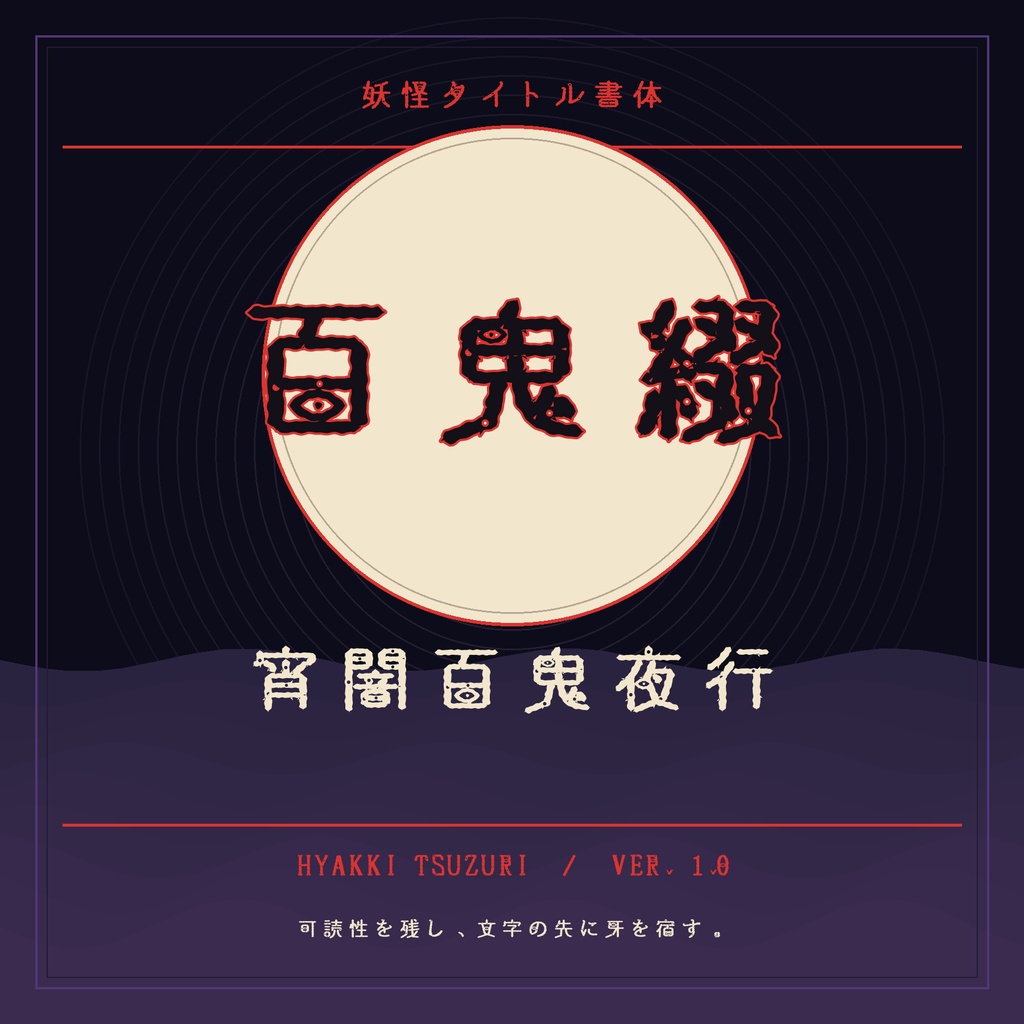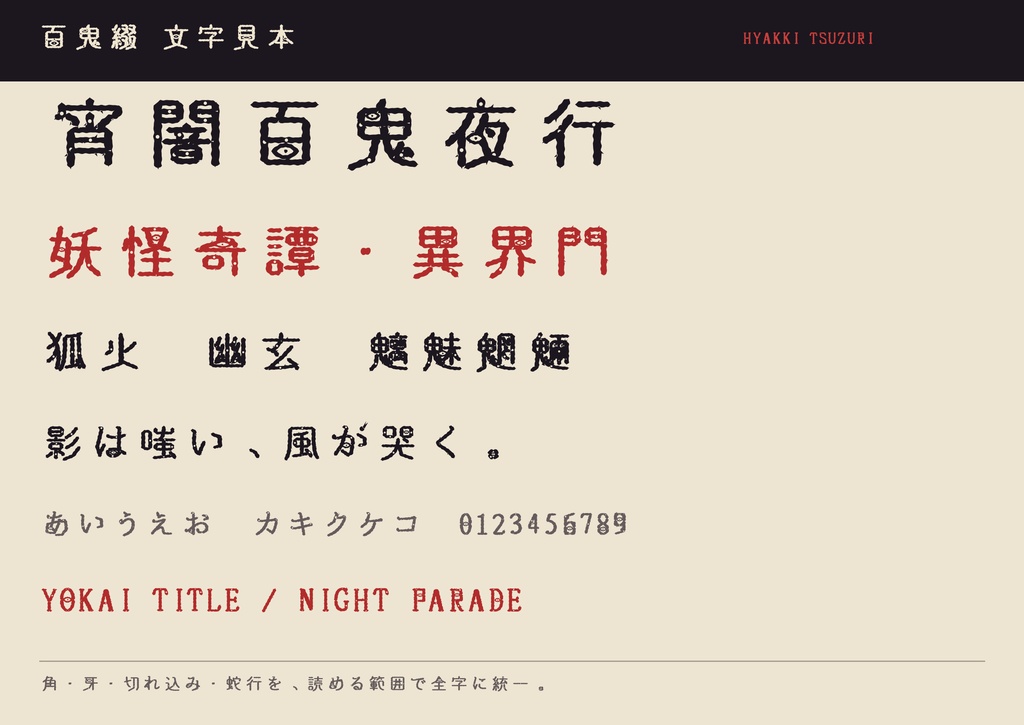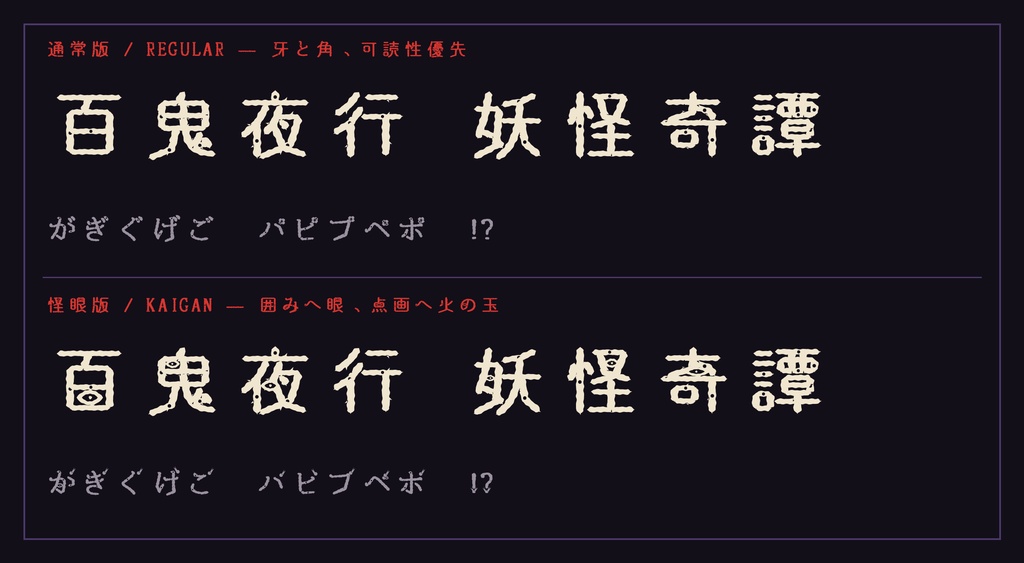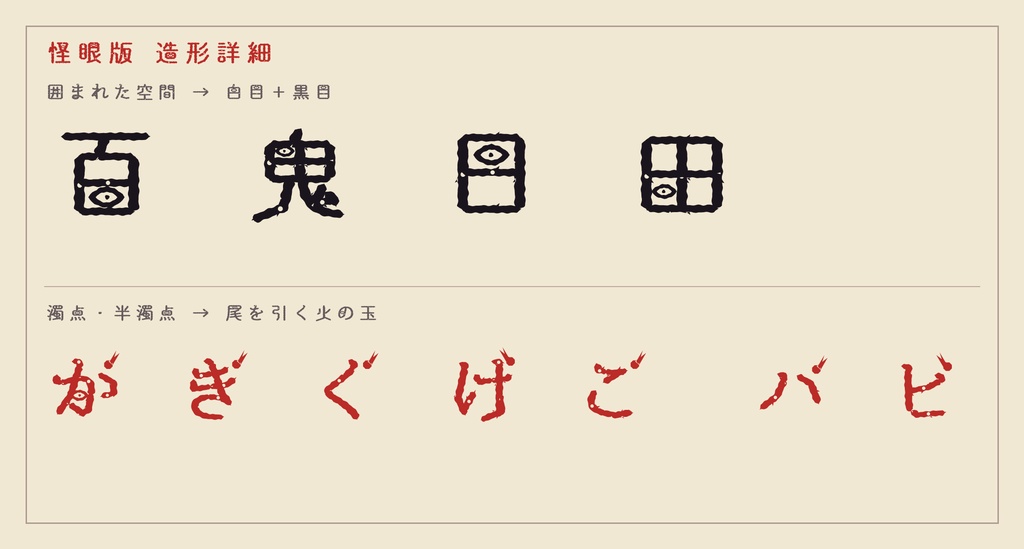
【百鬼綴】妖怪・和風ホラー向け日本語フォント|英字カナ版・常用漢字版
文字の先に牙を、輪郭に怪異を。 「百鬼綴」は、妖怪・和風ホラー・ダークファンタジー・怪談などのタイトルや見出し向けに設計した日本語ディスプレイフォントです。 ■ 2つの収録版 ・簡素版(英字・かな) 380円 英数字、ひらがな、カタカナ、基本的な約物を収録。漢字は未収録です。 ・常用漢字版 980円 英数字、ひらがな、カタカナ、常用漢字2,136字をすべて収録。さらに「魑魅魍魎」「鵺」「祟」「憑」「髑髏」など、妖怪・怪談タイトル向けの漢字も追加しています。 ■ 特徴 ・遠目では力強く読め、近づくと角・牙・切れ込みが見える二段階の表情 ・ランダムな汚しではなく、全字に統一した造形ルール ・通常版に加え、囲まれた空間へ眼、点画へ火の玉を置く「怪眼版」を同梱 ・商用作品、ロゴ、動画、配信、ゲームへの使用可 ■ 収録形式 TrueType(TTF)2種 / Windows・macOS ・Hyakki Tsuzuri Regular:可読性優先 ・Hyakki Tsuzuri Kaigan:ロゴ向け怪眼・火の玉仕様 ■ おすすめ用途 妖怪、和風ホラー、怪談、TRPG、祭、アニメ・ゲームのタイトル、サムネイル、章見出し、短い台詞など。 ※48px以上のタイトル・見出しを推奨します。 ※フォント単体の再配布・転売は禁止です。詳細は同梱の利用規約をご確認ください。